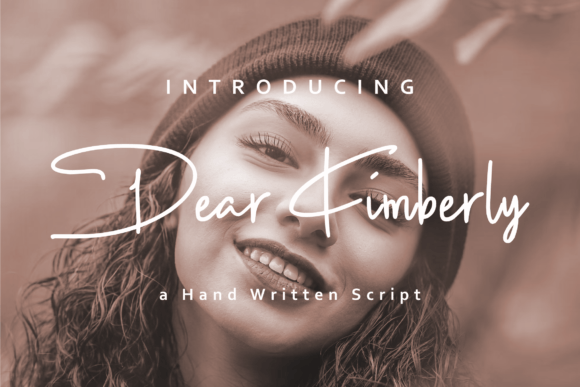
Dear Kimberly
適切なデザイン要素を見つけるのは難しい場合がありますが、Dear Kimberlyは作品を即座に引き立てる優れたコレクションを提供します。
POD(オンデマンド印刷)製品、結婚式の招待状、またはソーシャルメディアのグラフィックを作成している場合でも、Dear Kimberlyは理想的です。